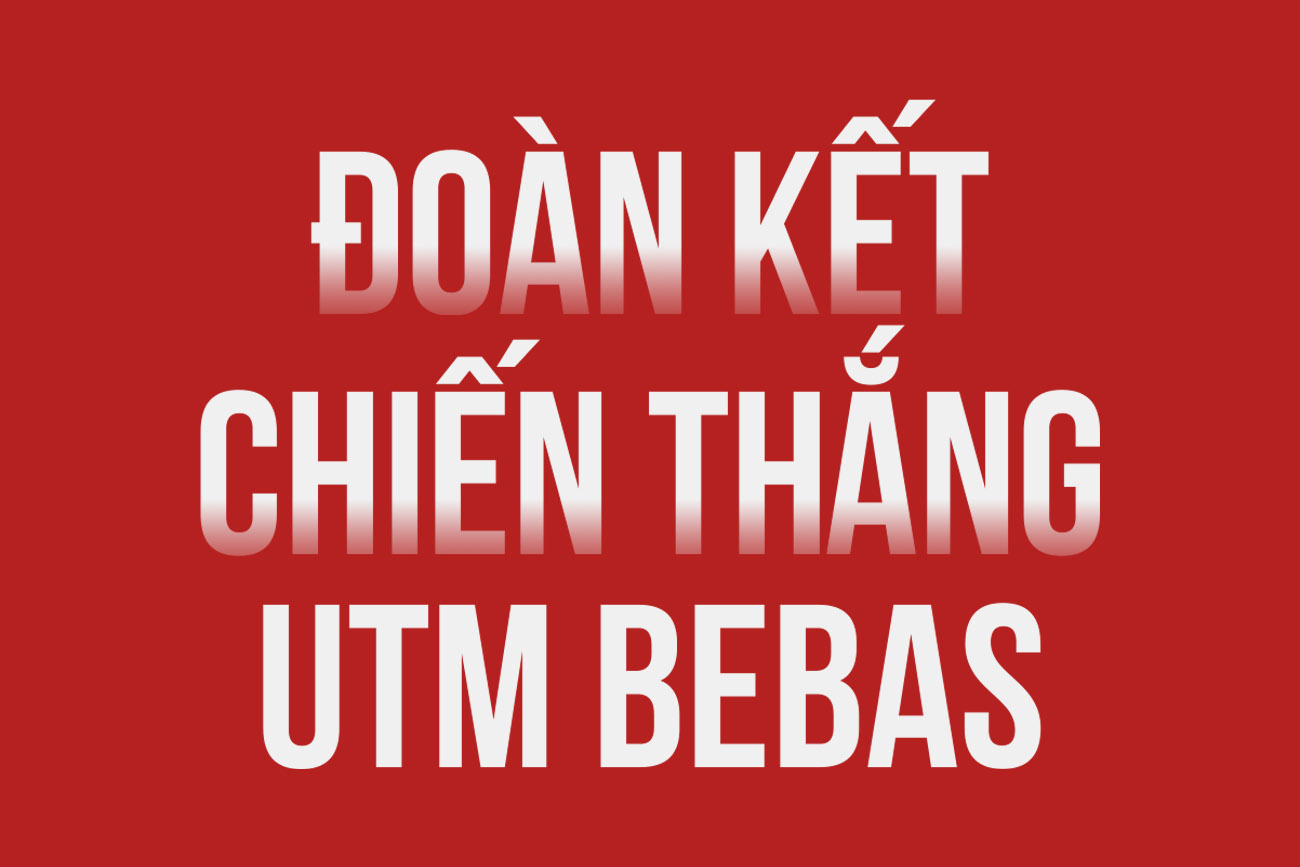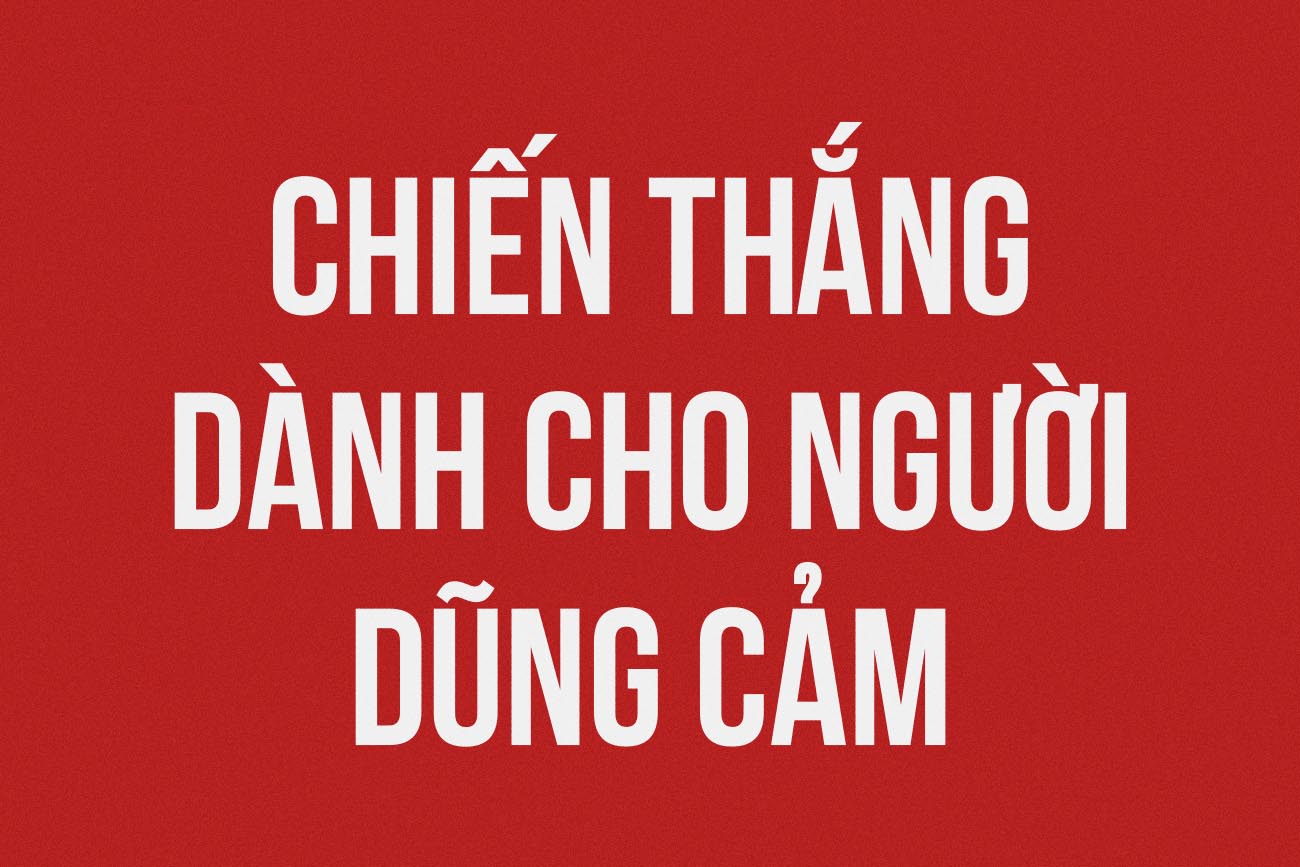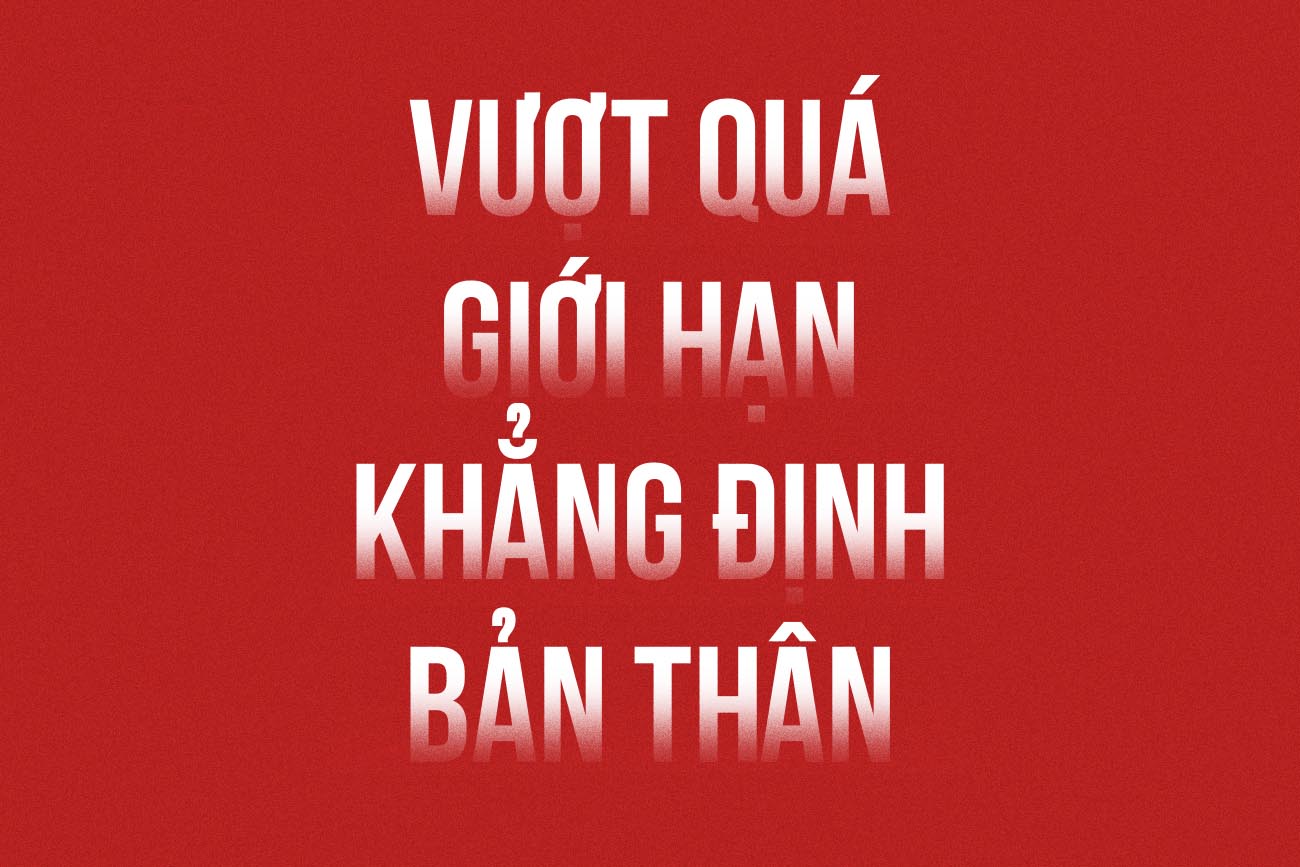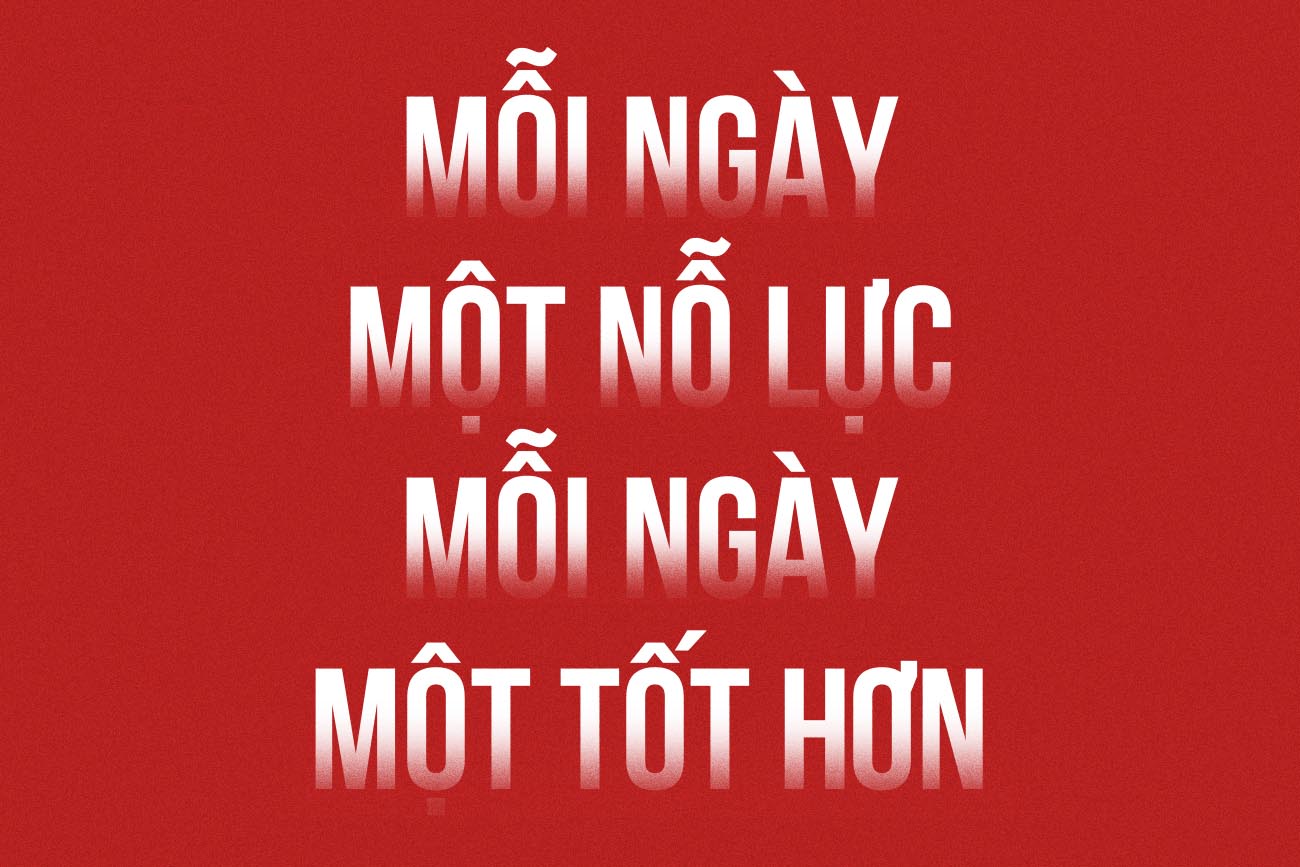
UTM Bebas là phiên bản Việt hóa của font chữ nổi tiếng Bebas do Ryoichi Tsunekawa thiết kế. Đây là một kiểu chữ sans-serif dạng display, được ưa chuộng trong thiết kế nhờ vào nét chữ in hoa toàn bộ, mạnh mẽ, dễ đọc và tạo điểm nhấn ấn tượng.
Đặc trưng nổi bật của UTM Bebas nằm ở các ký tự uppercase với tỷ lệ cao, đường nét thẳng đứng, độ dày đều nhau, mang đến cảm giác cân đối và chuyên nghiệp. Chính sự tối giản trong chi tiết đã giúp font này dễ dàng kết hợp với nhiều phong cách thiết kế khác nhau, từ hiện đại, tối giản cho đến công nghiệp hoặc thể thao.
Font đã được Team UTM Việt hóa hoàn chỉnh, hỗ trợ đầy đủ dấu tiếng Việt với dấu thanh cân đối, không lỗi hiển thị. Điều này cho phép các nhà thiết kế áp dụng UTM Bebas linh hoạt trong cả thiết kế in ấn và digital, đảm bảo vừa thẩm mỹ vừa chuẩn ngôn ngữ.
Với phong cách mạnh mẽ, rõ ràng, UTM Bebas là lựa chọn lý tưởng cho:
Tiêu đề poster và banner sự kiện
Bảng hiệu, biển quảng cáo
Bìa tạp chí, sách và ấn phẩm truyền thông
Logo hoặc slogan thương hiệu